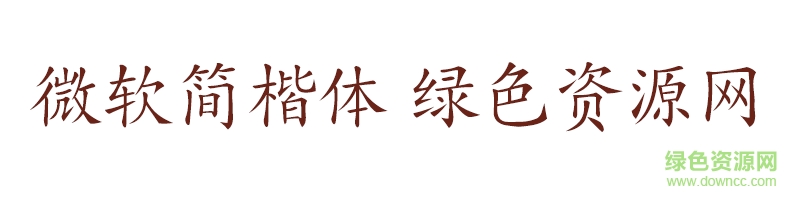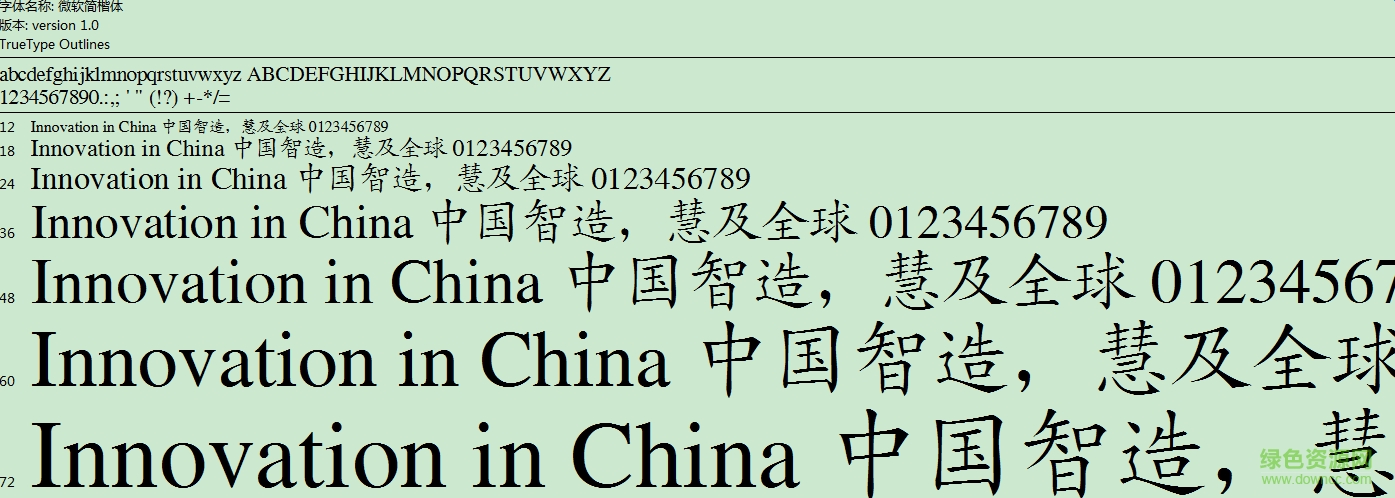
微軟簡楷體字體是一款微軟出品的簡體楷體字體,非常適合與文章、段落書寫、標題書寫等方面,小編為大家提供免費下載地址。歡迎大家來綠色資源網(wǎng)踴躍下載哦!
微軟簡楷體是一款非常端正的楷體字體,字形簡潔大方,效果十分漂亮。此款字體適用于包裝設(shè)計、廣告設(shè)計、海報設(shè)計等視覺環(huán)境。